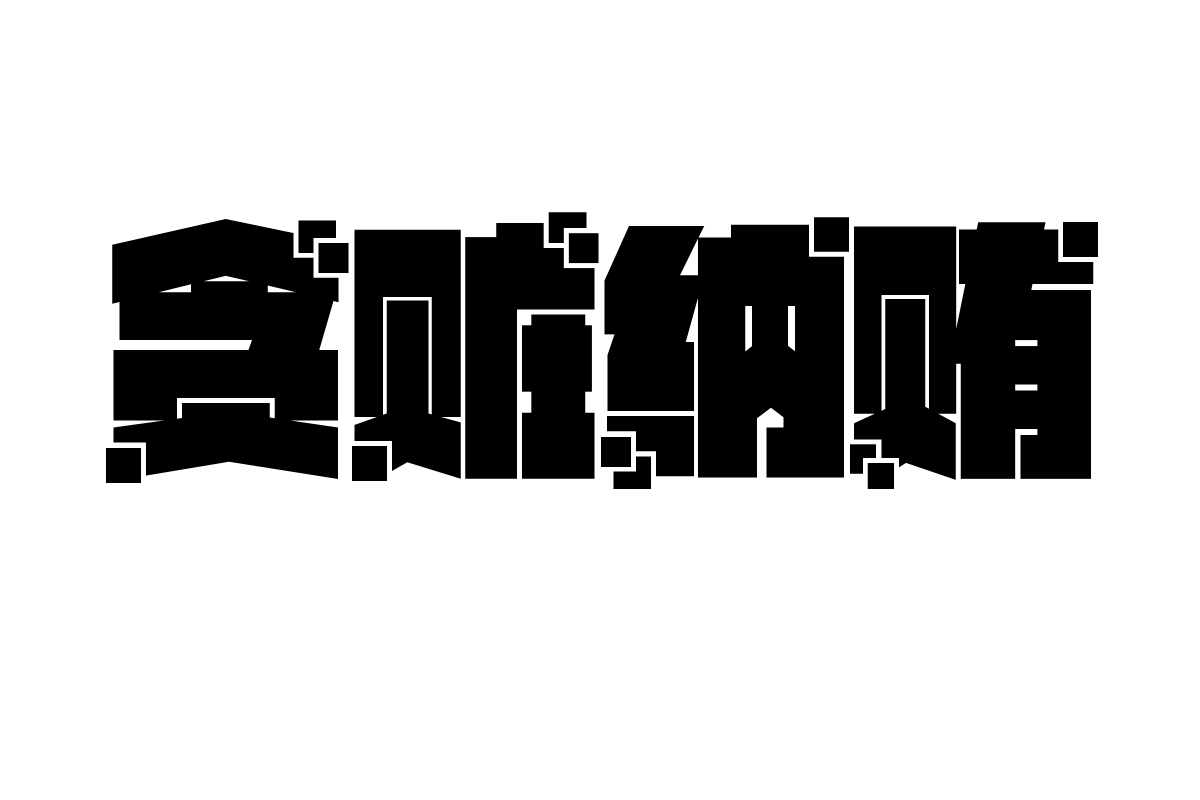
锐字太空夺宝像素简是一款简约风格的中文字体,由锐字公司设计。这款字体具有独特的风格和特点,适合用于需要简洁、现代感的应用场景,如网页设计、广告宣传、产品包装等。
锐字太空夺宝像素简的特点如下:
1. 字形独特:这款字体采用了独特的笔画结构和形状,使得每个字符都呈现出独特的视觉效果。同时,字体中的一些笔画还进行了简化处理,使得整体字形更加简洁。
2. 风格现代:锐字太空夺宝像素简的设计灵感来源于太空元素,使得整个字体充满了科幻气息。这种风格非常适合用于科技、游戏、电子等相关领域的应用。
3. 易读性强:由于字形简单,这款字体在阅读时不会显得过于复杂,有助于提高信息的传递效率。这对于需要快速阅读的场景尤为重要。
总之,锐字太空夺宝像素简是一款适合现代、简洁风格的中文字体,适用于各种需要简洁、现代感的应用场合。